¡Muy buenas! Hoy traigo ansia viva, alimento para bestias, el elixir de la vida. Hacía mucho tiempo que no os recomendaba un bundle de tipografías y ya es el momento de hacerlo. No lo había hecho hasta ahora porque no había visto ninguno que me pareciera suficientemente completo, pero hoy sí. Agarraos, id preparando espacio en vuestro ordenador, porque os podéis ir de aquí bien cargaditos.
los bundles son grandes recopilaciones de recursos, en este caso de tipografías que, durante un tiempo limitado, te permite conseguir un montón de productos por menos precio.
Hacía mucho tiempo que no os recomendaba un bundle de tipografías. Lo cierto es, que la mayor parte de meses, traen tipografías bastante similares. Yo suelo mirar cada mes, a ver si hay algo que me interesa y creo que, las tipografías del bundle de abril, os pueden interesar. Las tipografías son variadas, traen muchísimas decoraciones y textos alternativos, así que puede ser una buena inversión.
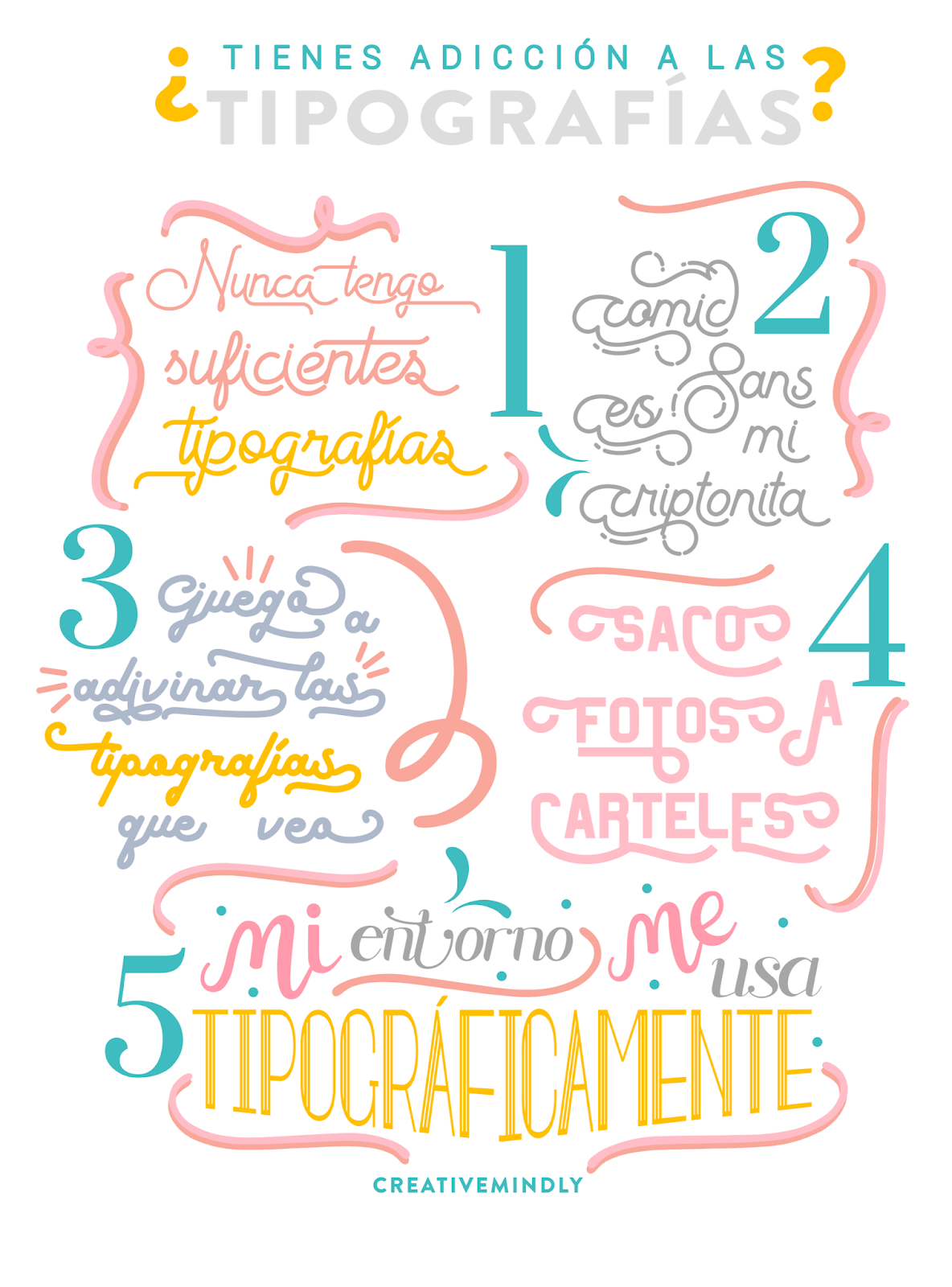
este diseño lo he hecho utilizando varias de las tipografías que incluye el bundle, junto con un tutorial, nuevo y exclusivo, que tendrán todos mis alumnos de los cursos de tipografías. He añadido tres vídeos nuevos.
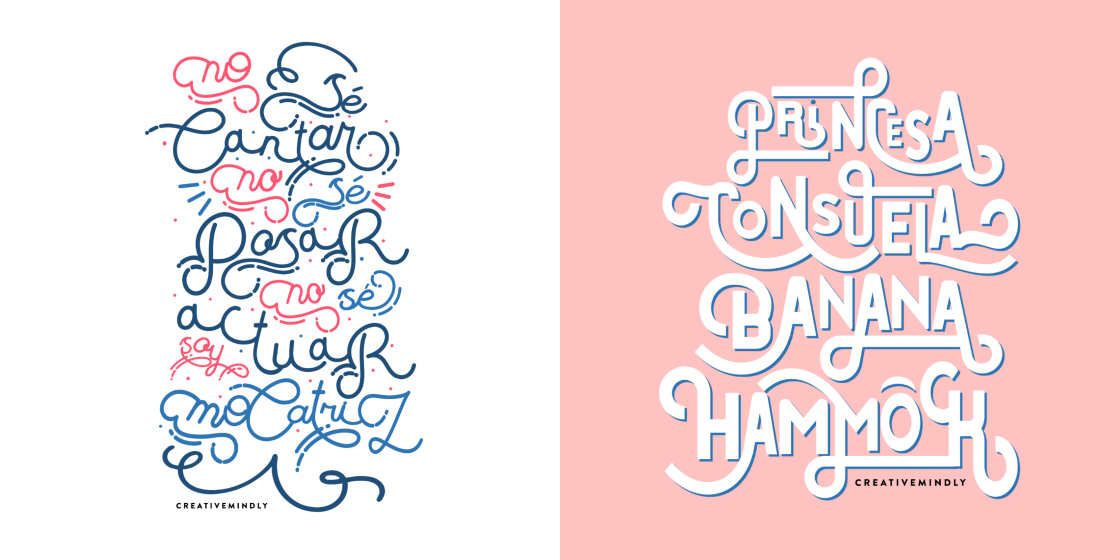
En los cursos que os he dejado arriba, como os decía, he añadido 3 vídeos nuevos donde, además de contaros una nueva técnica para trabajar con las tipografías que acabo de descubrir, os enseño a hacer los dos carteles que tenéis aquí: Mocatriz y Princesa Consuela. Si esto no os engancha al diseño con tipografías, nada lo hará.